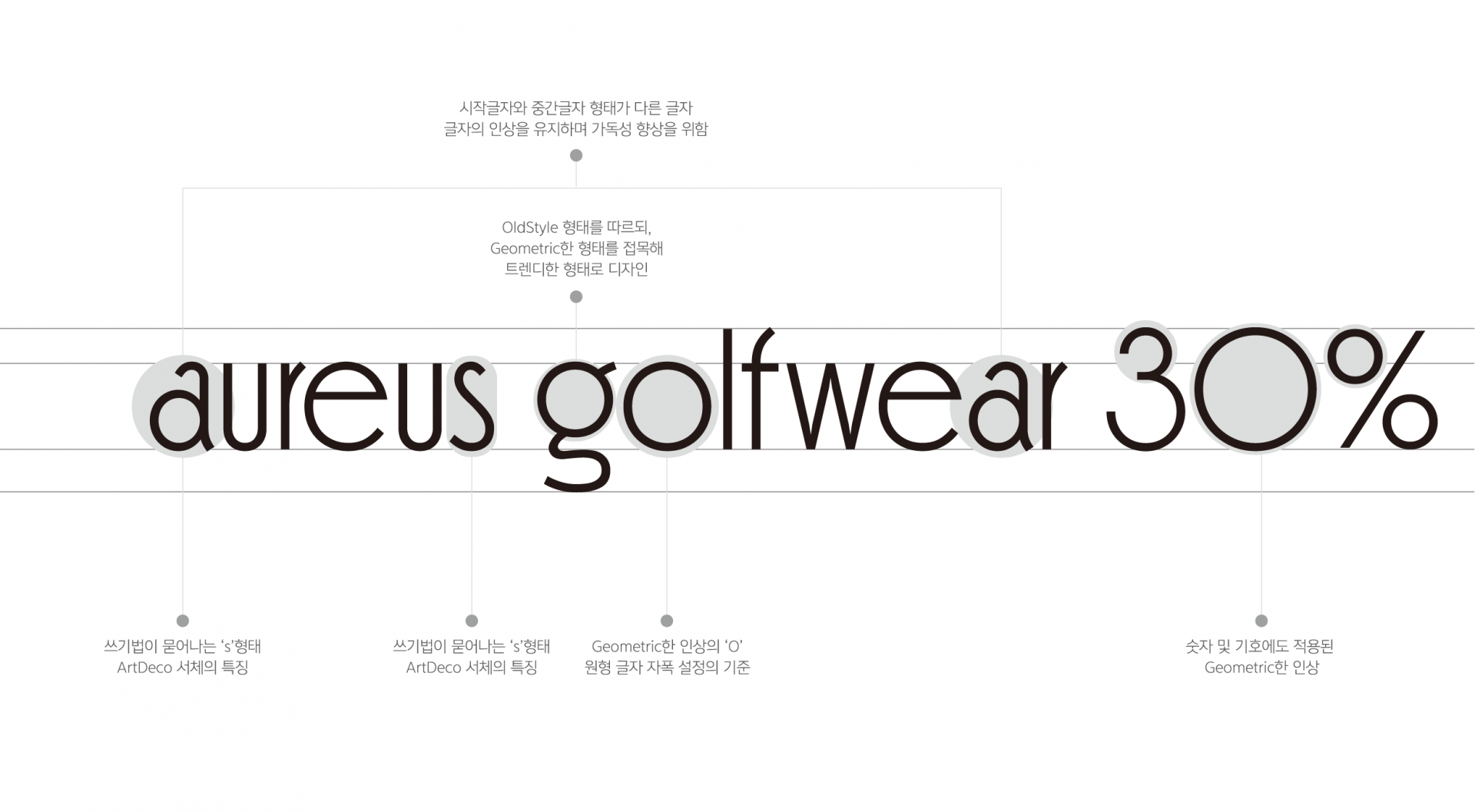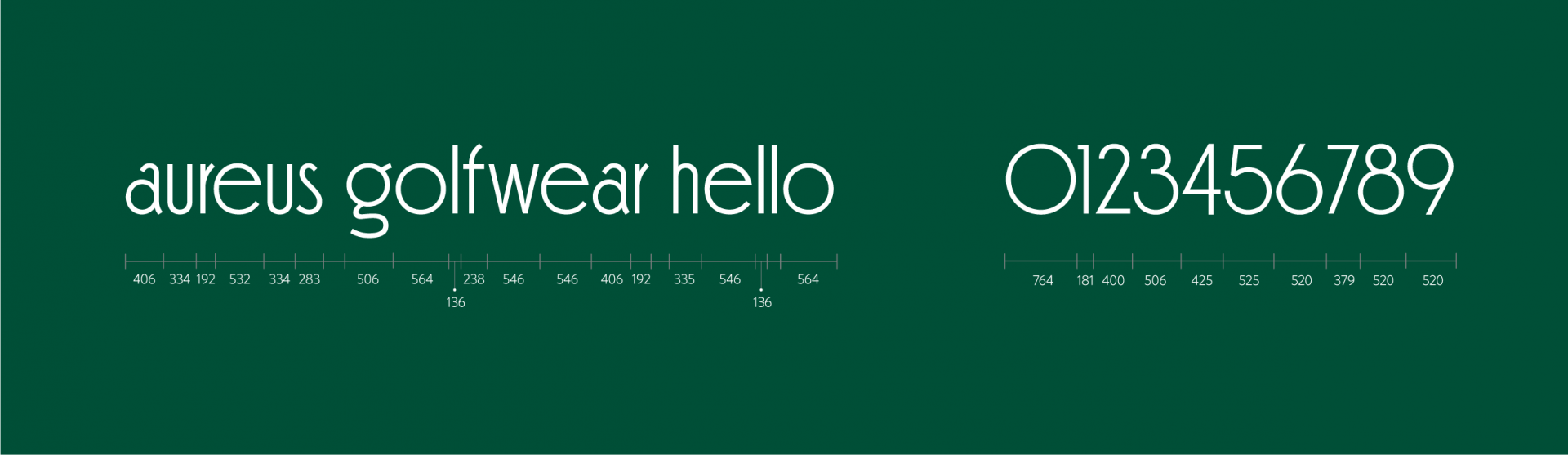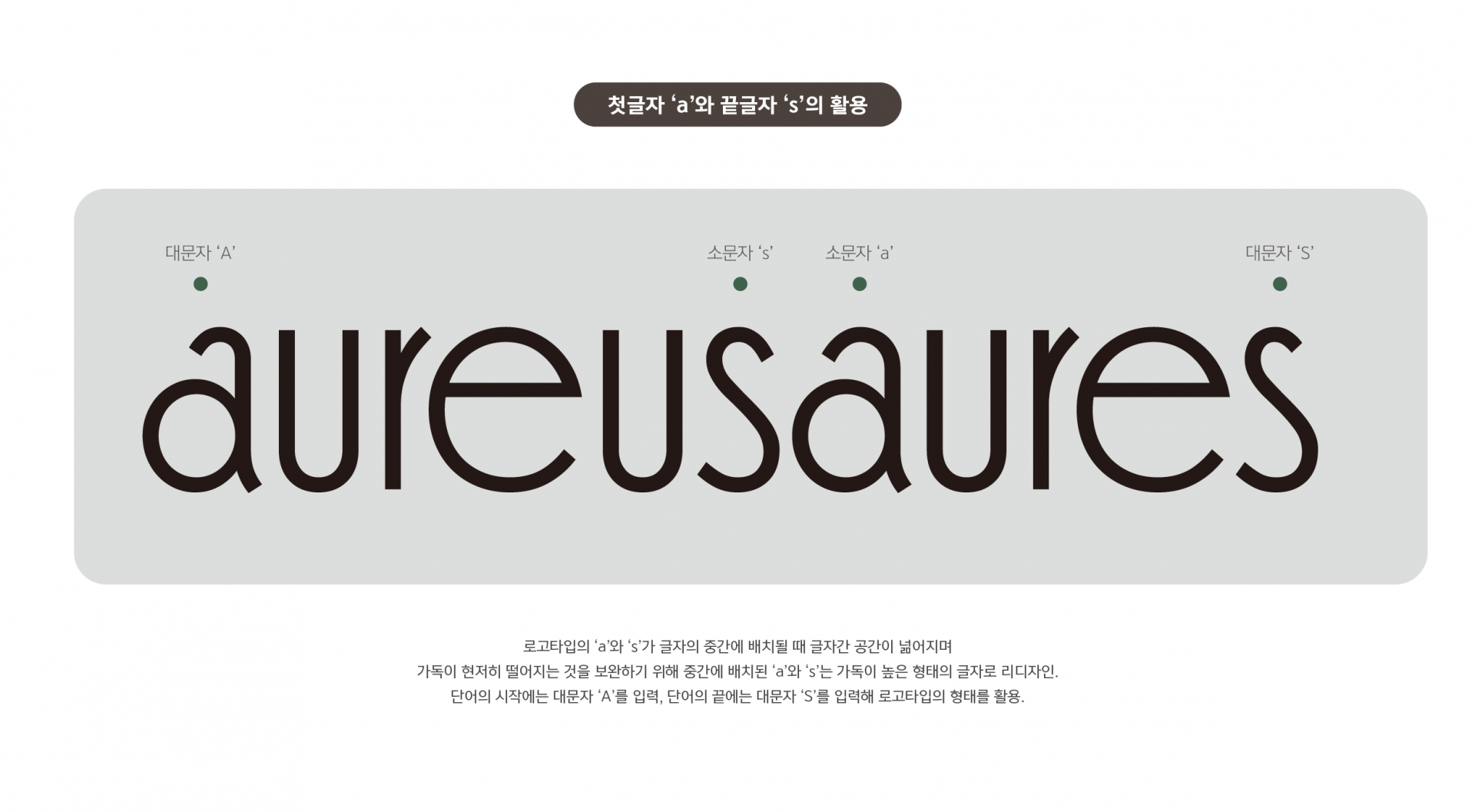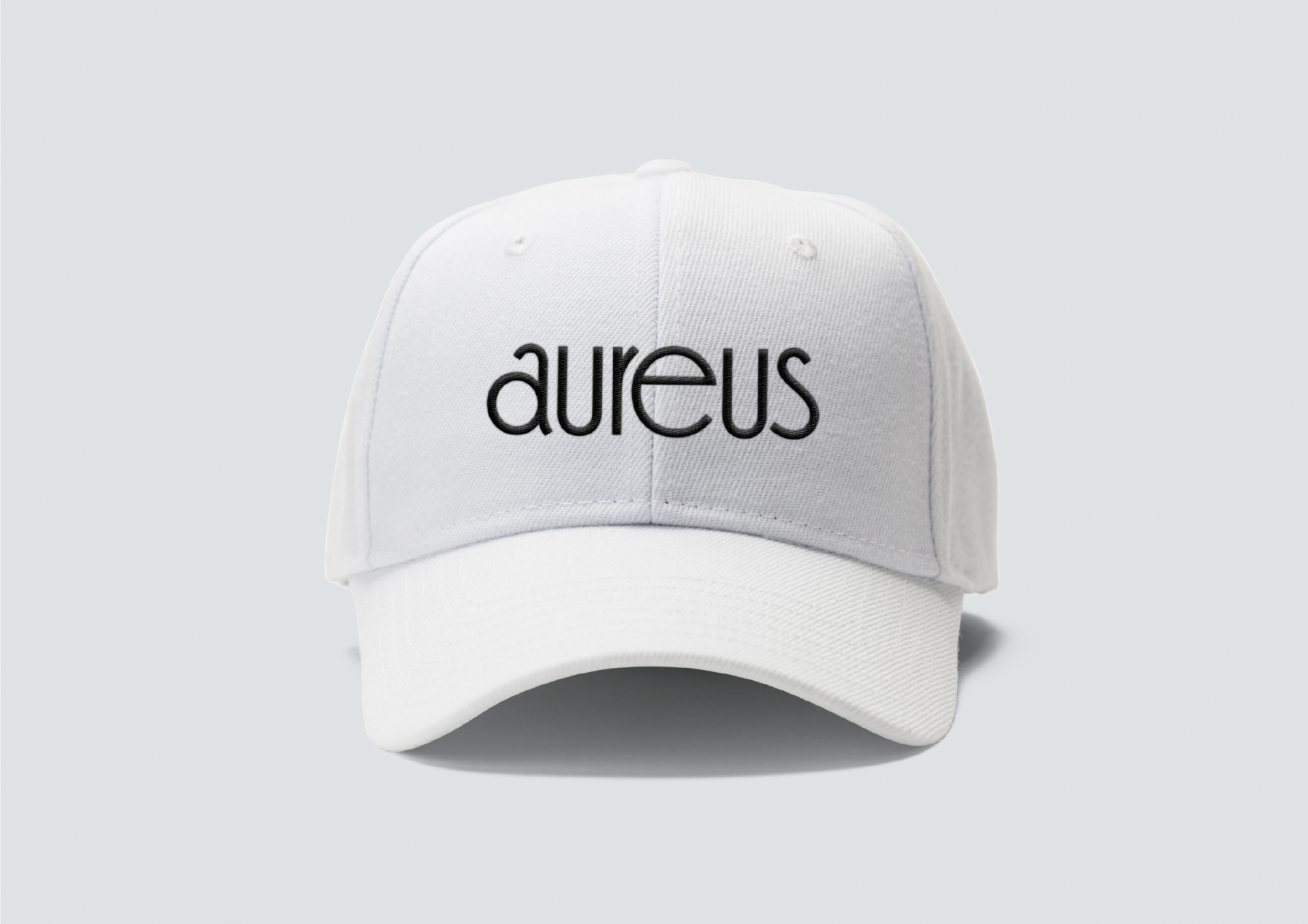
aureus [aureus]
aureus 서체는 1970-80년대 미국 골프웨어 시장을 주름잡던 aureus의 로고타입에서 파생된 서체이다. Geometric한 글자와 쓰기법이 묻어나는 글자가 함께 공존하는 것이 특징이며, 글자 간 큰 자폭차이로 시각적인 강렬함과 주목성을 전한다.